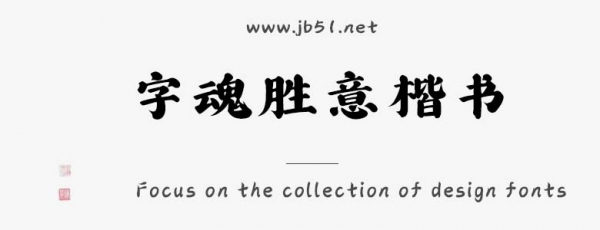
字魂勝意楷書體是由字魂字庫推出的毛筆書法字體,該字體包含9503個中文、字母、 符號和數(shù)字,具有國風(fēng)手寫的風(fēng)格,適合應(yīng)用于藝術(shù)設(shè)計、平面宣傳設(shè)計、網(wǎng)頁設(shè)計,書法字帖等領(lǐng)域。
字魂勝意楷體字體是一款商用的毛筆書法,書法字字體,該字體包含9503個中文、字母、 符號和數(shù)字,具有國風(fēng)手寫的風(fēng)格,可以滿足您設(shè)計上的各種需求,該字體主要用于電商直播等場景, 您不但可以在字魂網(wǎng)下載字魂勝意楷體字體,同時還有眾多毛筆書法字體、創(chuàng)意字體等可供選擇!